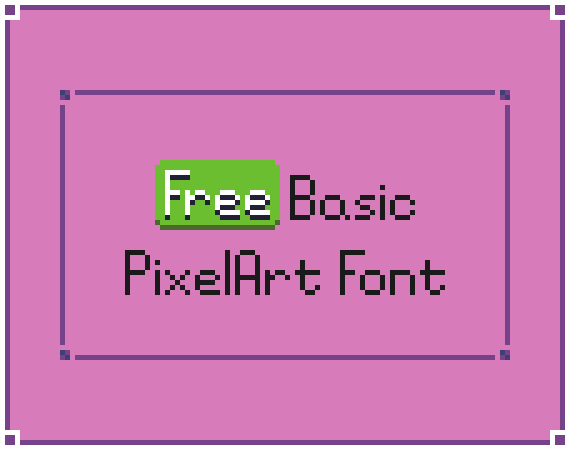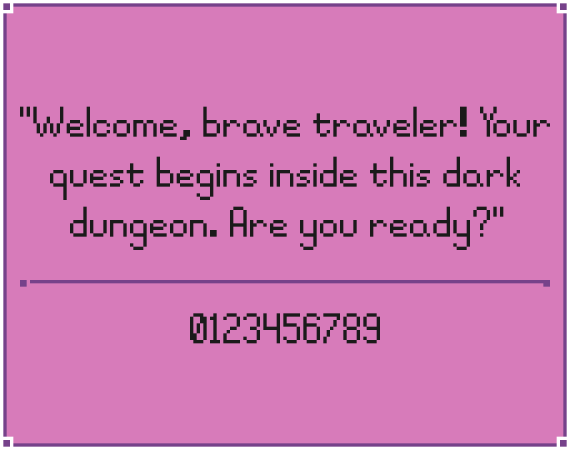
简洁经典的免费基础像素字体素材,专为游戏开发者和数字艺术家设计。它非常适合复古角色扮演游戏、平台游戏、文字密集型对话以及复古用户界面。
它简单易用,毫不花哨,而且完全免费。
支持的字符:
ABCDEFGHIJKLMNÑOPQRSTUVWXYZ ÁÉÍÚÓÚ
abcdefghijklmnñopqrstuvwxyz áéíóú ü
0123456789 !¡”#$%&'()*+,-./:;<=>¿?@[\]^`{|}~°±½¼¾
简洁经典的免费基础像素字体素材